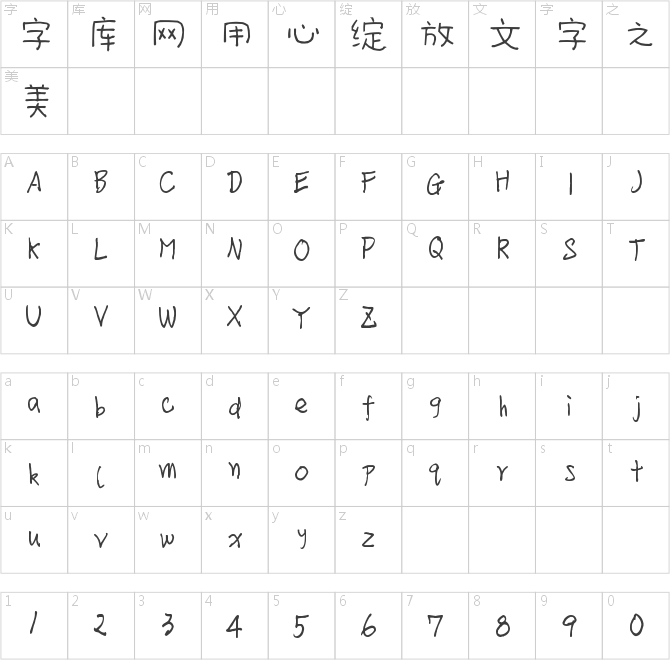
方正泡泡體 詳情頁
字體名稱: 方正泡泡體
一款優秀的字體往往在部件的設計羅輯上是統一的。方正泡泡體的部件設計無疑是優秀的,特別是口、日等封閉部件的處理,具有代表性。另外該字在大小上進得特別設計,使得該字排版看起來活潑、輕快,有一定的韻律與節奏感,就像隨風飄舞的泡泡。適用于青少年兒童類、文藝類書刊、漫畫綜藝字幕、品牌廣告和產品包裝設計,以及社交網絡的個性化用字。